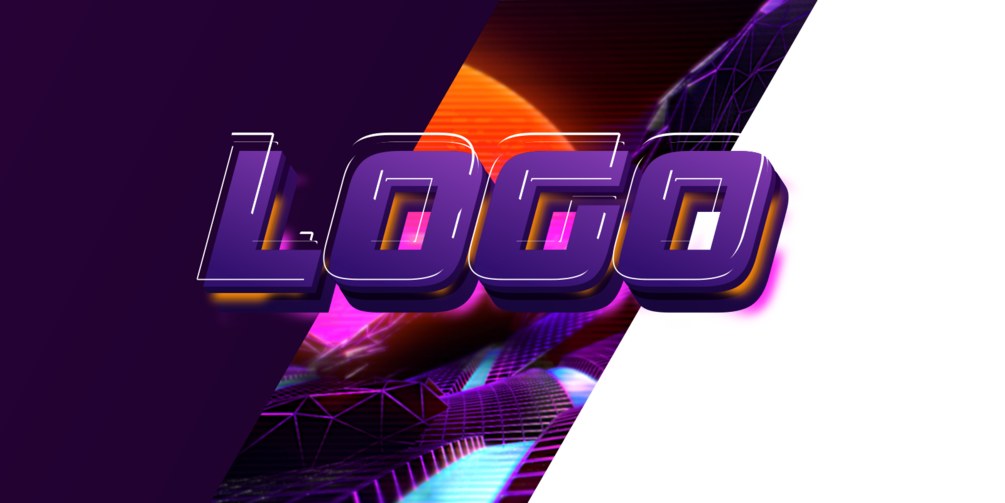
Text logo effect Многослойная объёмная надпись с элементами неона для шапки канала или видео превью, оформления групп, соцсетей и рекламы
cool text effect